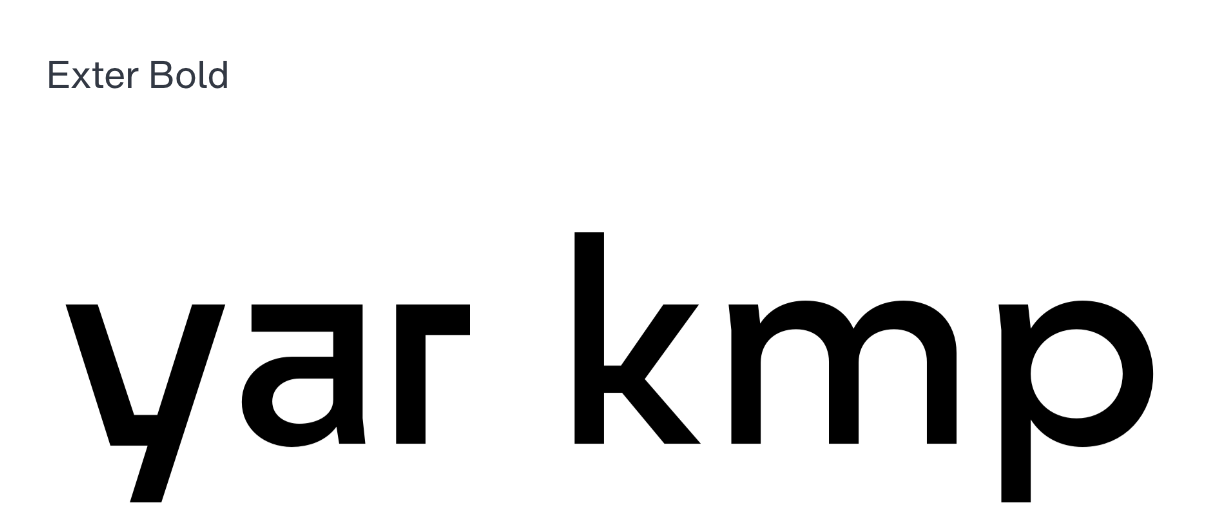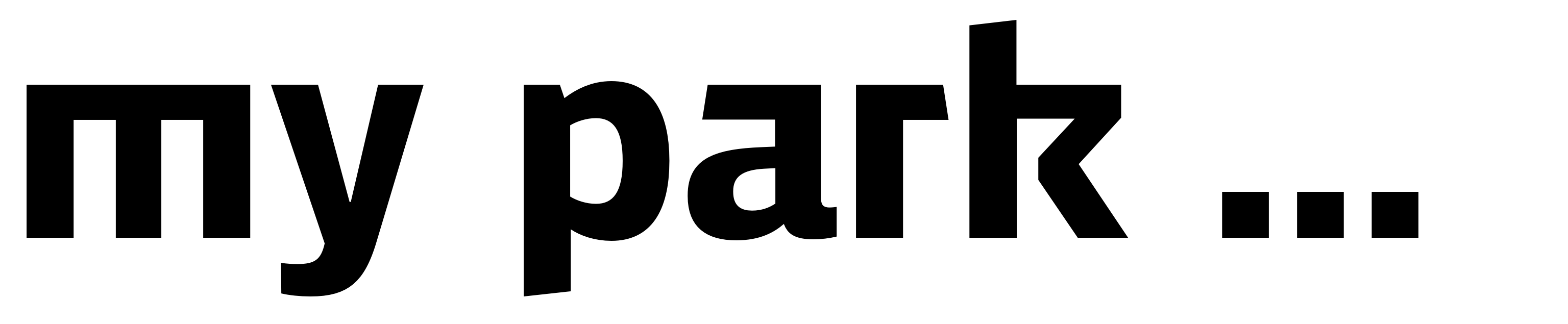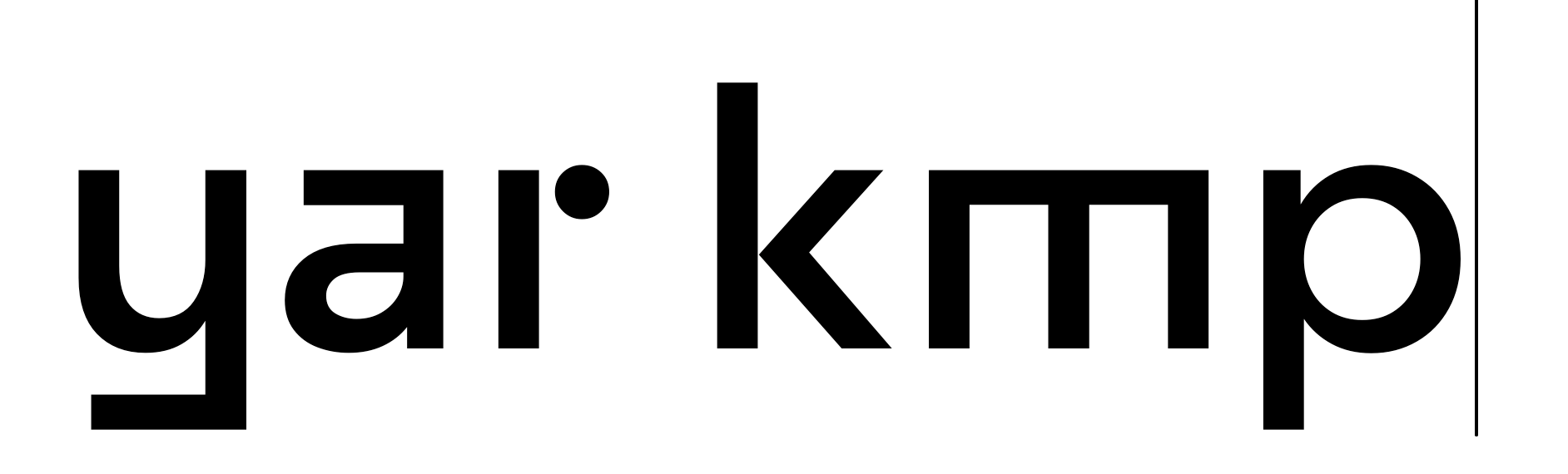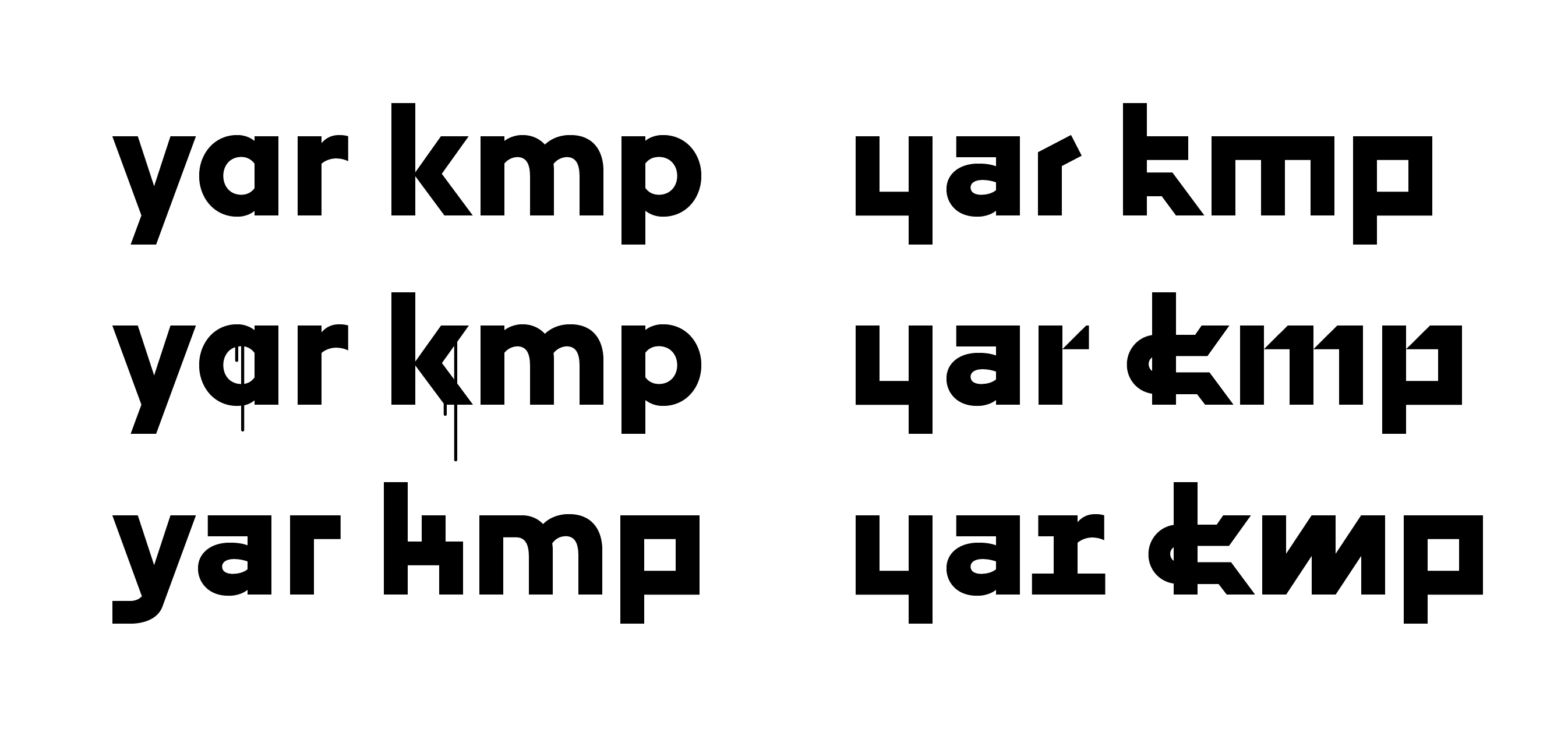
Ich suche eine Schrift, die ähnlich der Unytour oder Exter ist …
Wenn du auf das »y« verzichtest, bekommst du bei Stawix Ruechas Dalle zum Ausgleich ein passendes »m« und »k«.